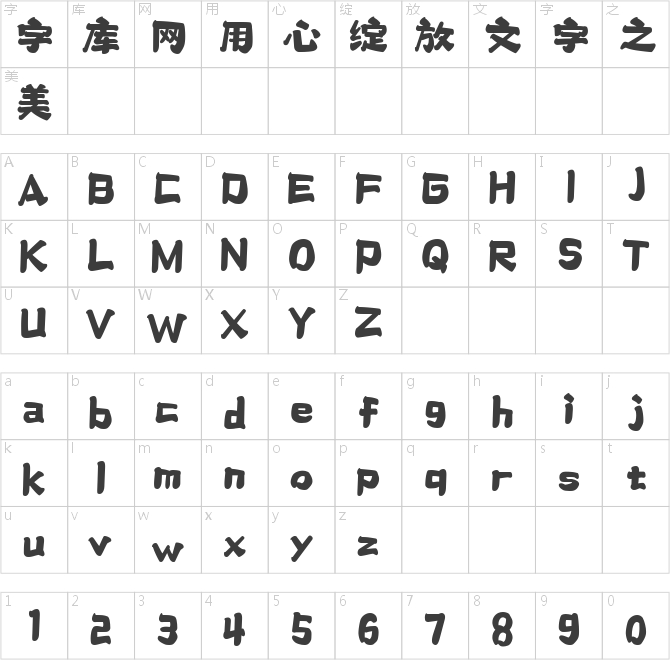
字體名稱: 一筆壹畫加油體
一筆壹畫加油體
簡介:一筆壹畫字工坊是一家專注于中文字庫開發的工作室,致力于做大家都用得起的正版字。工作室主創有十年字庫開發經驗,擅長創意、黑體、手寫等市場主流字體。
一筆壹畫加油體字體字庫是一款讓人賞心悅目、百看不厭的中文字體,適合各類廣告和產品包裝設計應用,字體大小8.83MB,格式為ttf字體,上傳用戶是一筆壹畫字工坊,作者/版權方為一筆壹畫